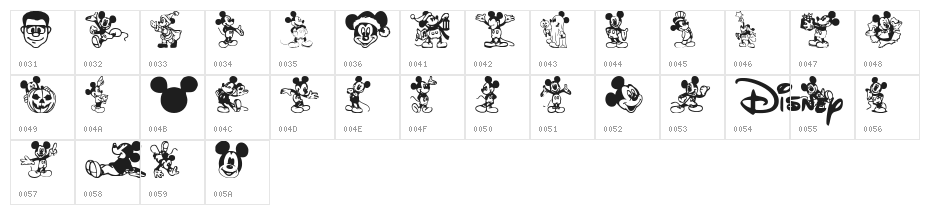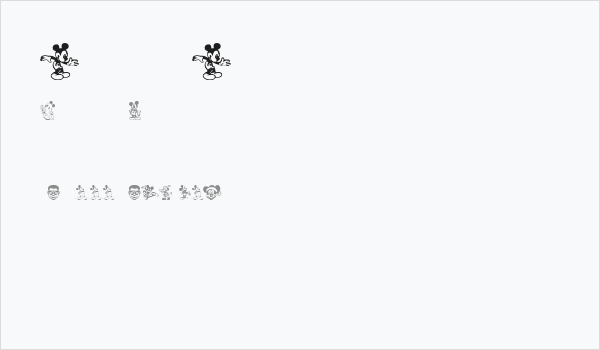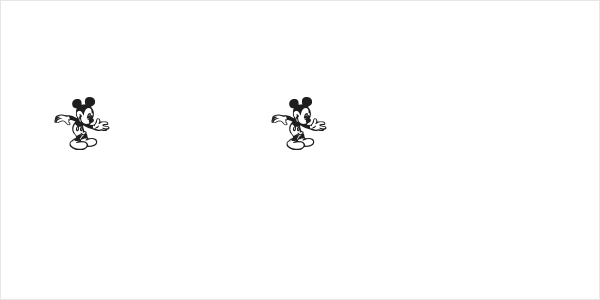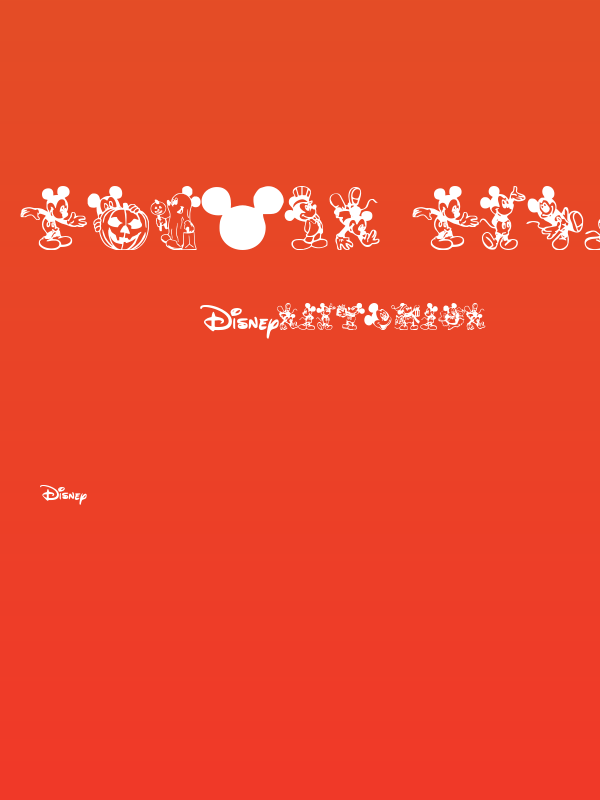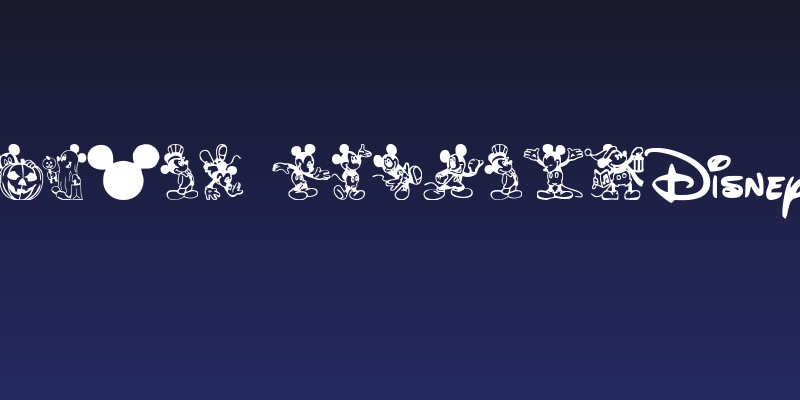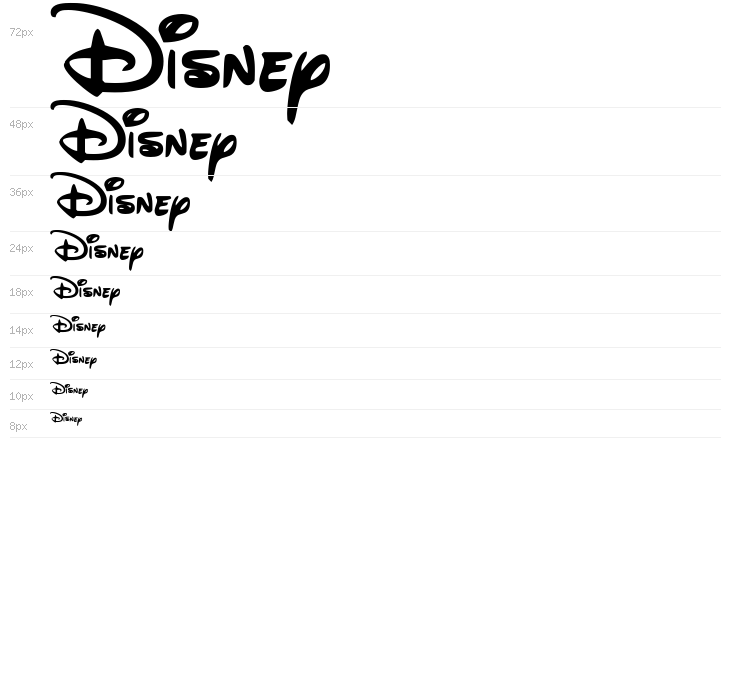
Mickey Mousebats Font
| Gesamtstil | Playful, Decorative, Cartoon |
| Anwendungsfall | Logos, Posters, Invitations, Themed Graphics |
| Vorgeschlagene Projekte | Children’s party invitations, themed event flyers, scrapbooking, playful branding, educational materials. |